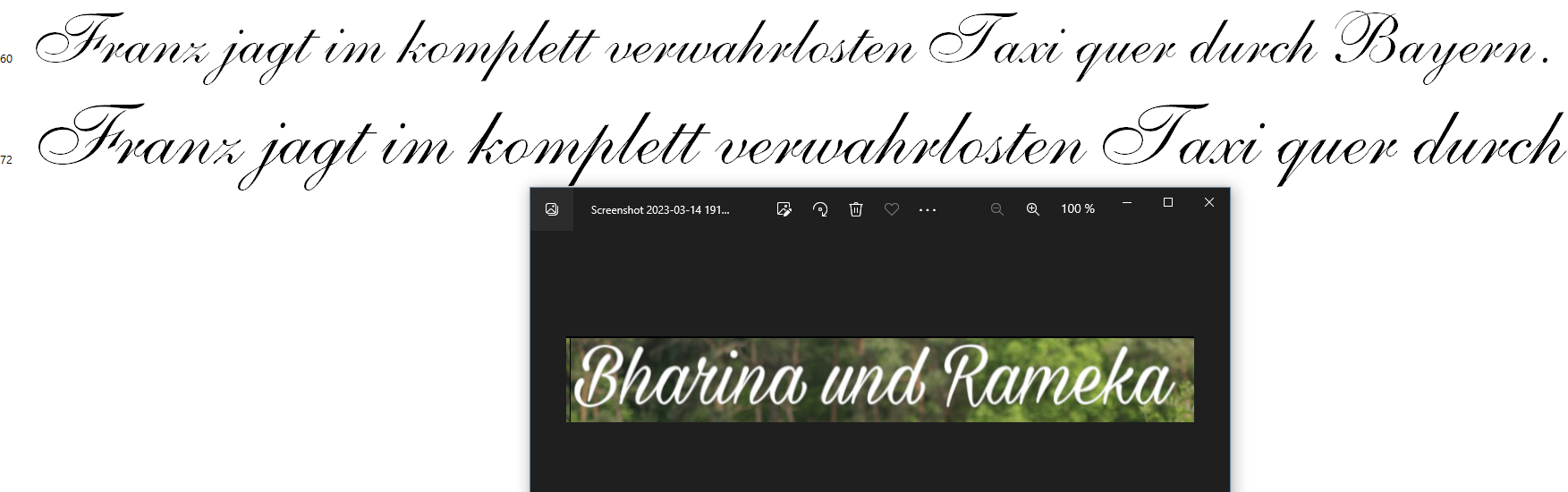
Welche Schriftart ist das ?
Nach stundenlanger vergeblicher tool suche, bin ich jetzt hier gelandet, weil ich umbedingt wissen möchte, was diese 2 Schriftarten sind bzw wie sie heißen. Könnt ihr mir weiterhelfen bzw einen Namen in die Runde werfen ? :)
link?
ist das eingepettetes bild oder kann man in den quellcode schauen und nachsehen?
shelly allegro font ist auch nahe dran und war glaube ich bei corel draw mit dabei und gibt es kostenlos
@ThomasK_7 Naja, nicht wirklich nahe dran, da sieht man überall recht deutliche Unterschiede:
Falls es nicht die exakte Schriftart sein muss findet man aber sicherlich etwas und würde damit vermutlich auch zufrieden.
Das ist tatsächlich meine Seite ;) Gut gestalked :D
Und was ist mit der 2. Schriftart ?
Die darunter ? ;)
Edit: Wobei das r bei Bharina nicht korrekt ist, das k bei Rameka aber wiederum diesen Bogen nach oben korrekt hat. Irgendeiner dieser Angilla Fonts müsste es dann aber sein.
man sieht ja auch beim i und beim n deutlich, dass es nicht die passende Schrift ist. Und ja, das "r" habe ich auch immer gesehen, aber das war so weit auseinander, dass ich mir nicht sicher war, ob es wirklich ein r ist...